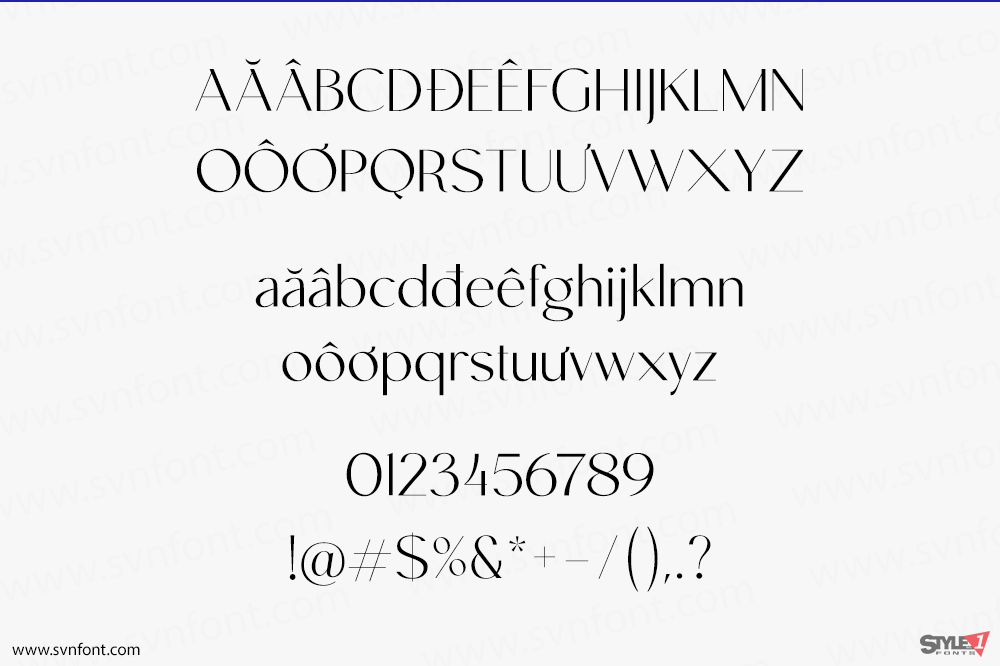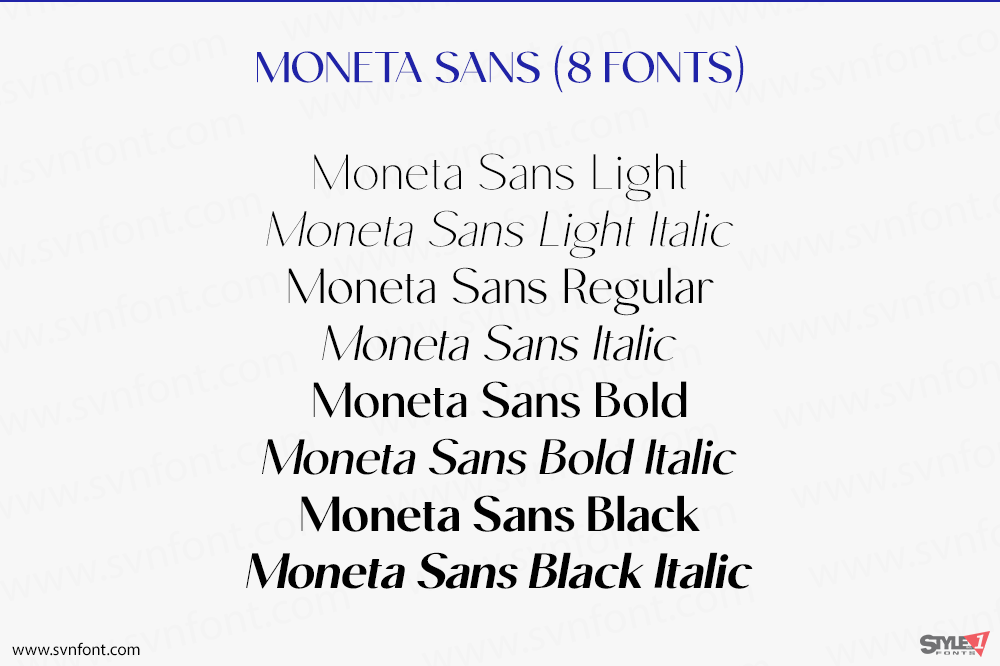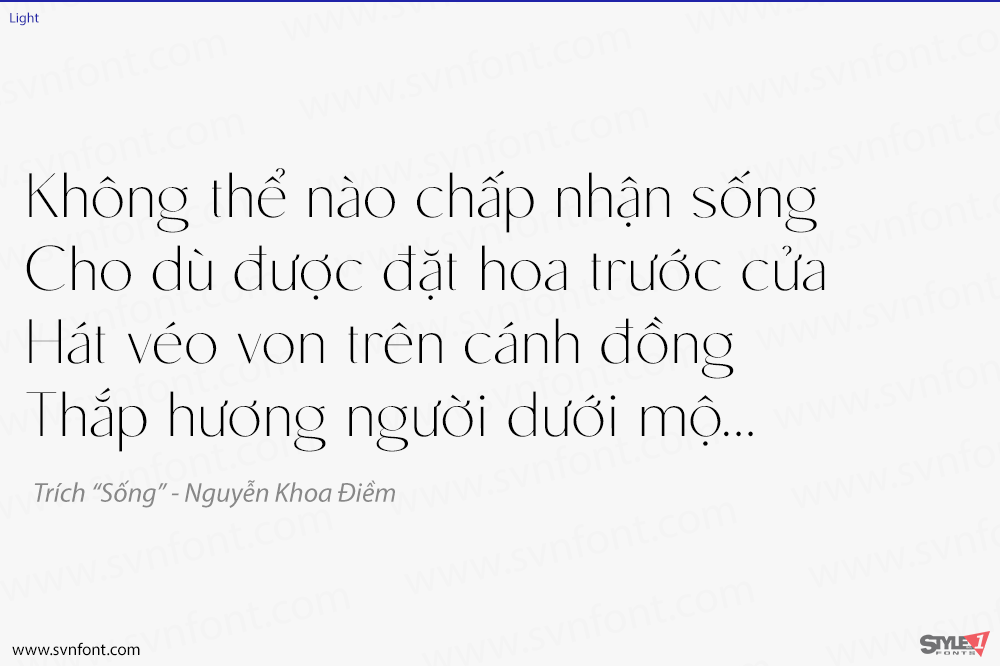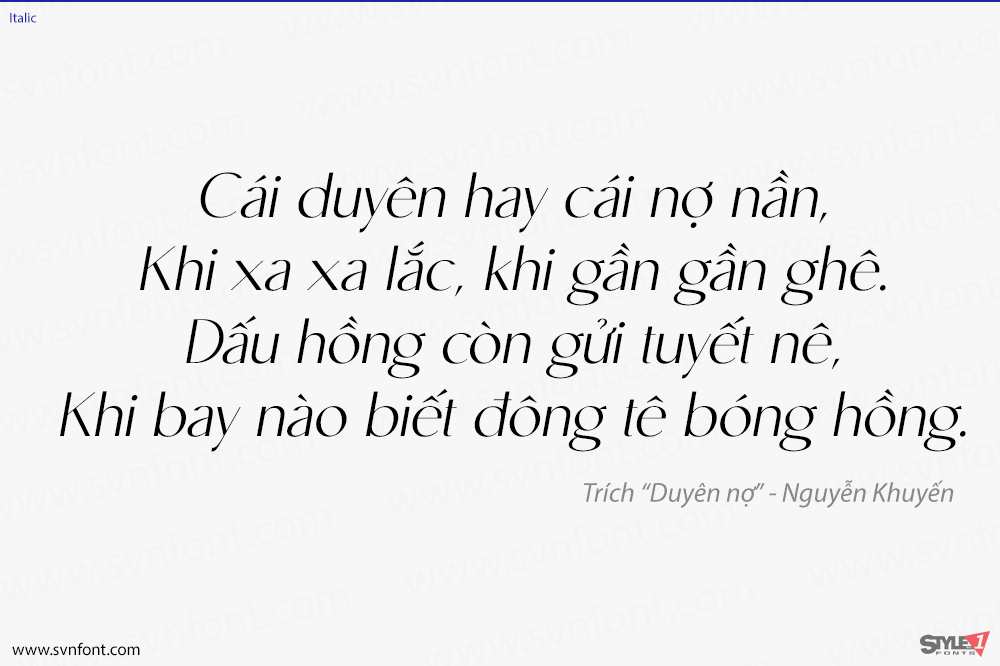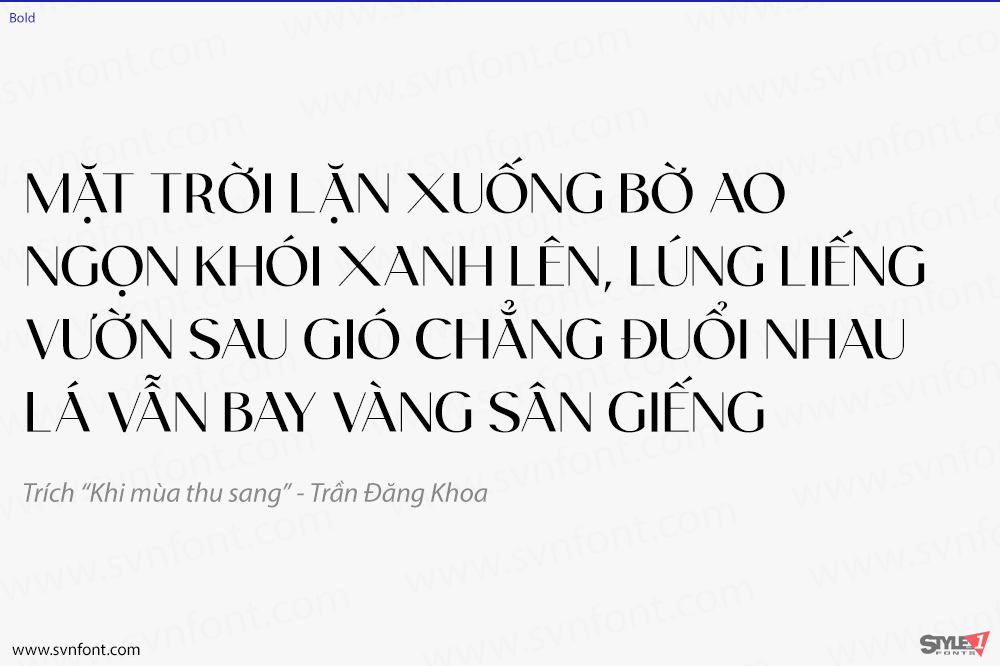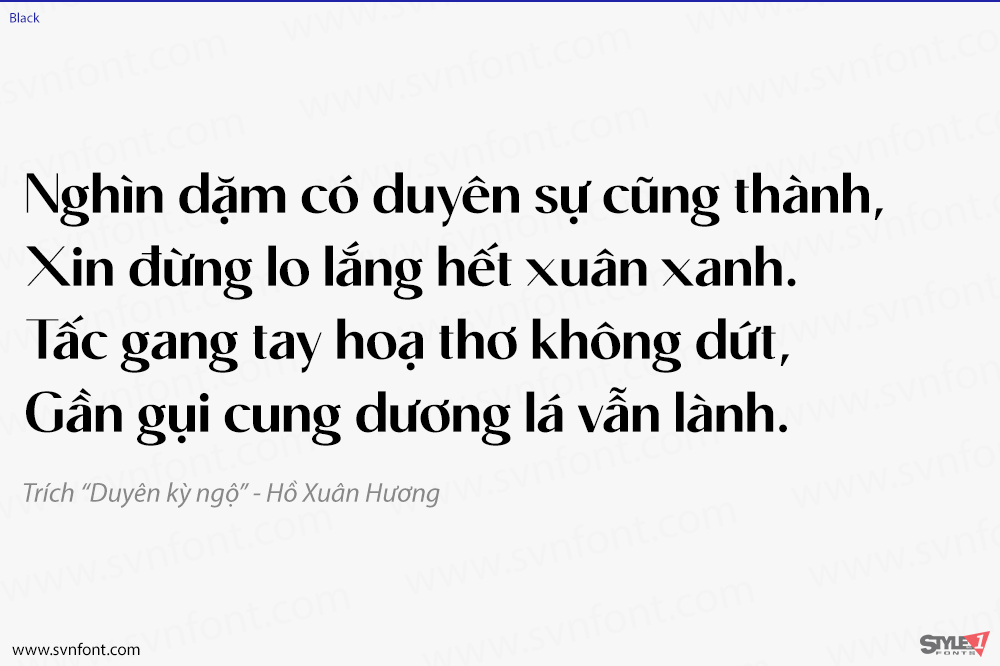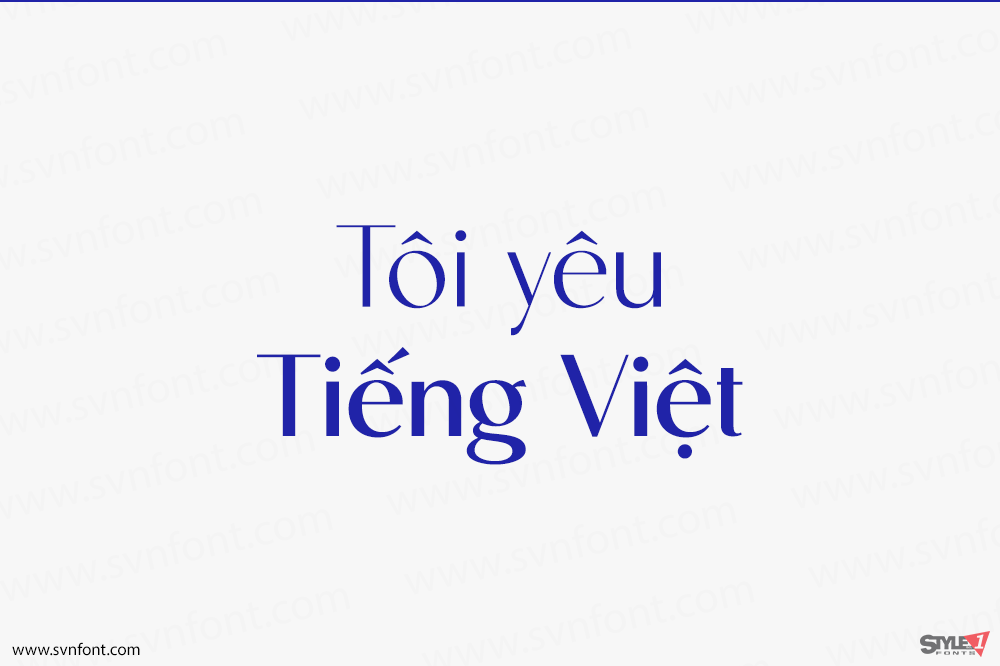
Moneta™ Sans là một kiểu chữ sans-serif chuyển tiếp trang nhã với độ tương phản cao. Hình thái của nó dựa trên nghiên cứu về các kiểu chữ viết tay truyền thống bằng bút ngòi rộng. Nó có 2 phong cách và 4 độ dày khác nhau (Light, Regular, Bold và Black).
Nhà thiết kế: Santi Rey
Nhà phát hành: Santi Rey